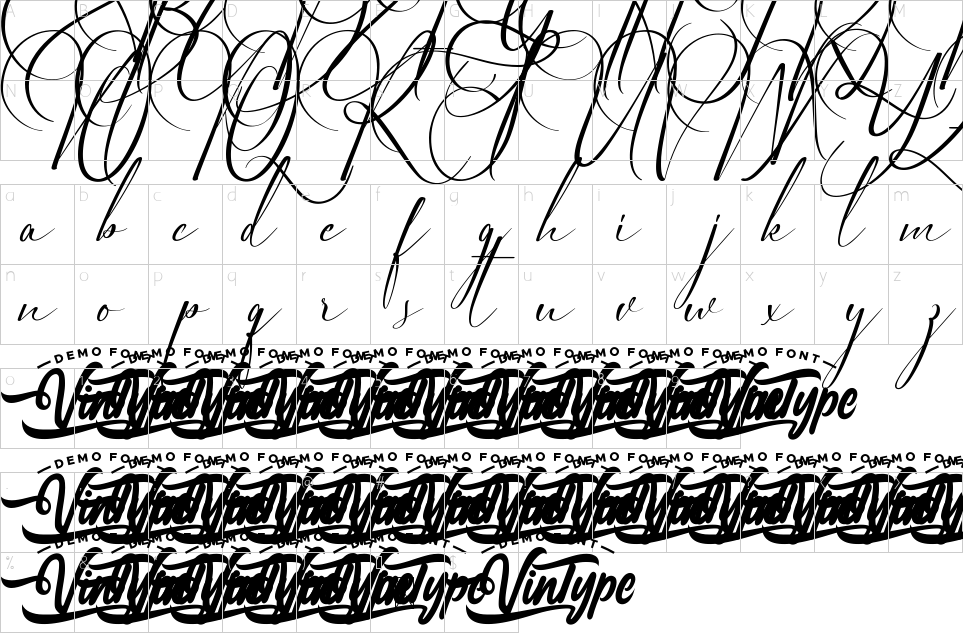
Anniversary Day Font – Download Grátis
A fonte ‘Anniversary Day’ é uma seleção de caracteres elegante projetada para tornar seus projetos ainda mais atraentes. Esta fonte foi criada por um designer anônimo, e já foi baixada 2,811 vezes. Com um design agradável e versátil, ‘Anniversary Day’ é perfeito para qualquer projeto que precise de uma fonte atraente e profissional. Seja para gráficos de desktop, designs de websites ou simplesmente para documentos de escritório, esta fonte é uma ótima escolha. Com sua simplicidade e sofisticação, ‘Anniversary Day’ é uma fonte gráfica que você não pode deixar de experimentar.